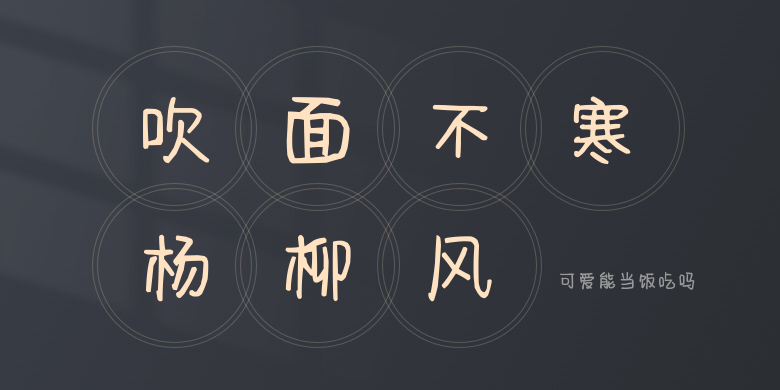
可爱能当饭吃吗
可爱能当饭吃吗,这款字体结构工整、笔画清晰,兼顾美观与易读性,适用于标题、正文、海报、包装、LOGO 等多种场景。字形优雅稳定,风格百搭耐看,适配日常排版与创意设计,让文字呈现更舒适、更具质感。可爱能当饭吃吗一笔一画,皆是细节,以均衡的比例、流畅的线条打造舒适视觉体验,字形端正大气,风格简约现代。无论是商业设计、品牌宣传还是日常排版,都能轻松驾驭,让文字更有格调与力量。可爱能当饭吃吗字体下载。